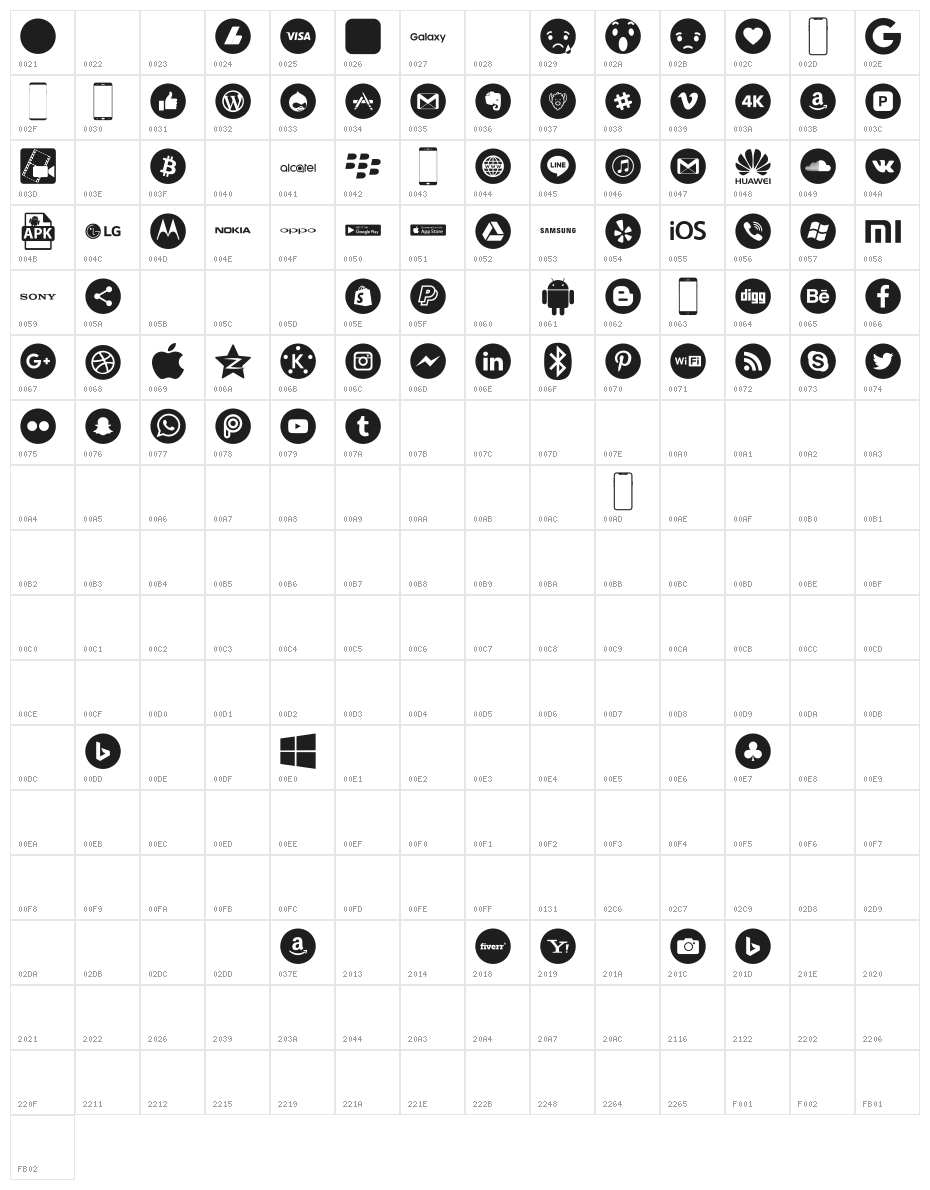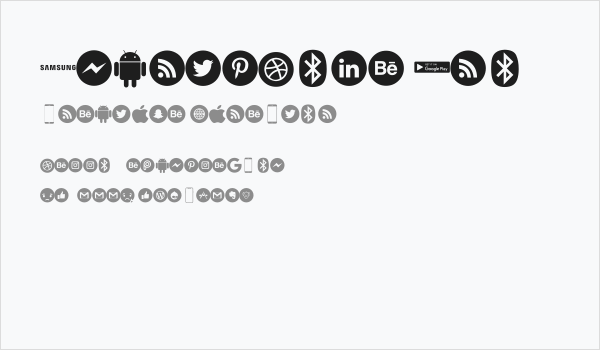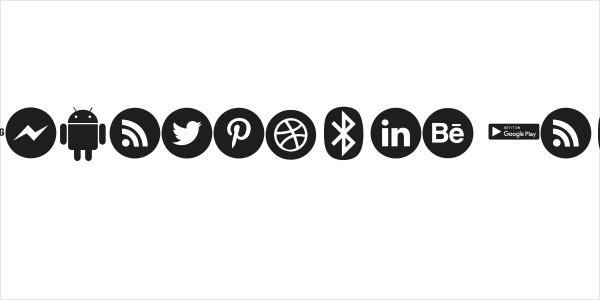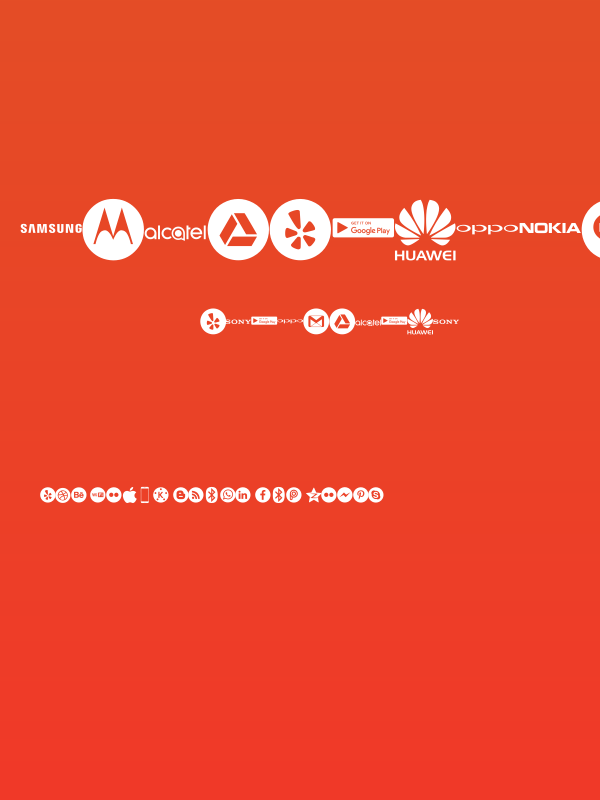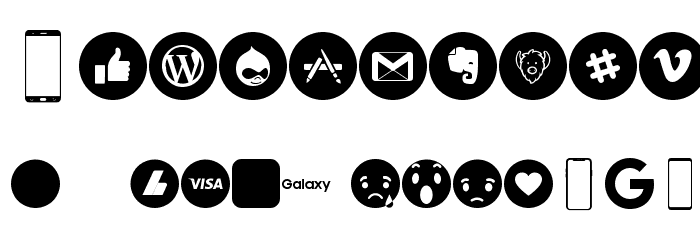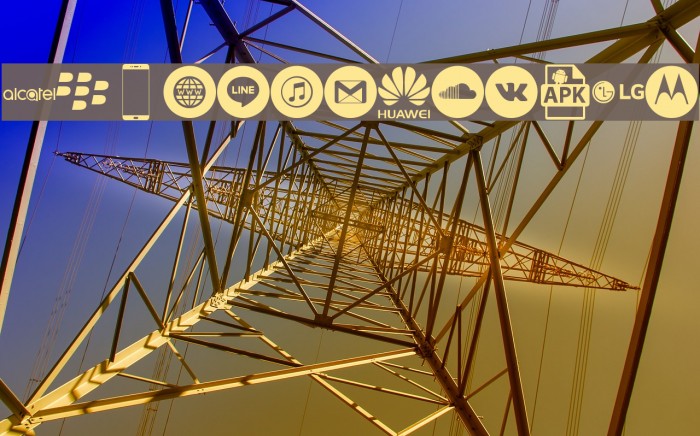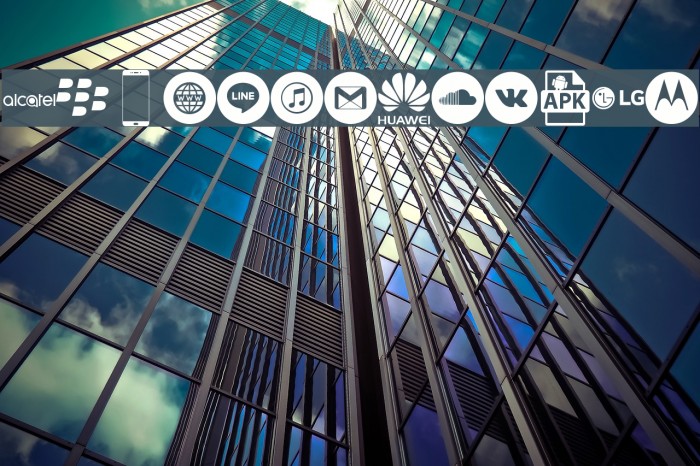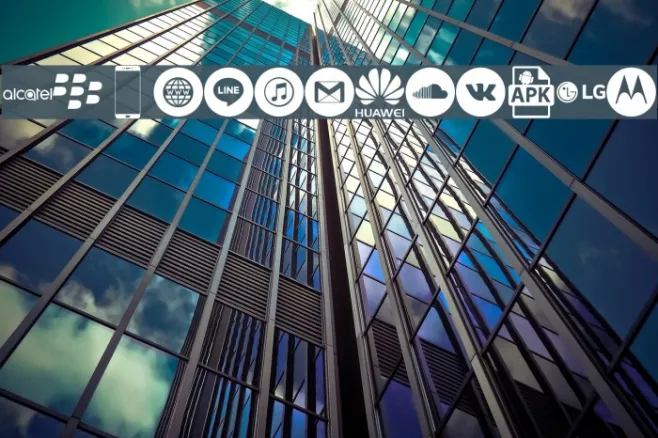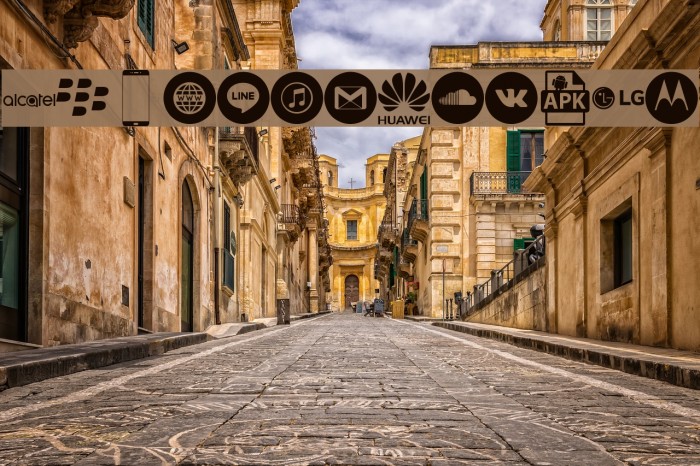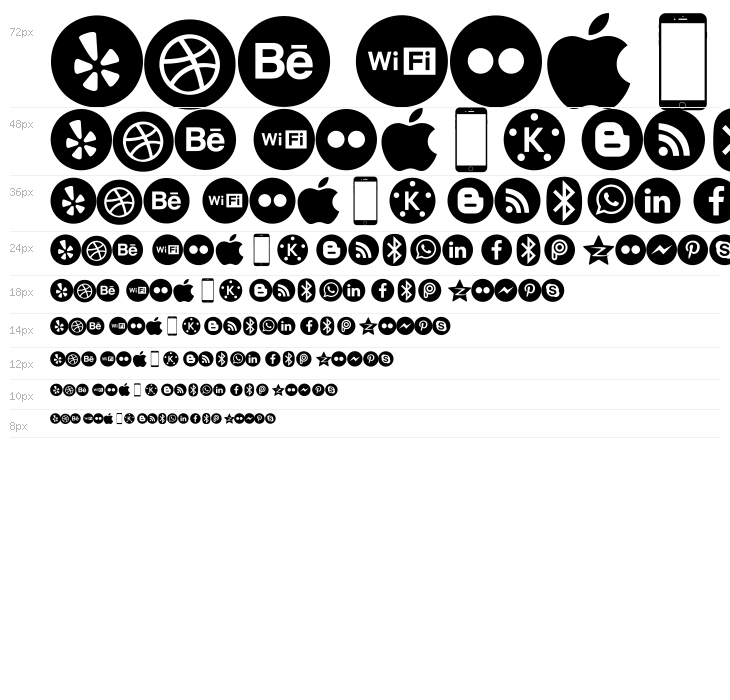
Smartphone Pro Font
| Estilo general | Modern, Minimalist, Decorative |
| Caso de uso | Icons, Logos, UI elements, App branding |
| Proyectos propuestos | App interfaces, tech branding, social media graphics, UI icon sets, presentations. |